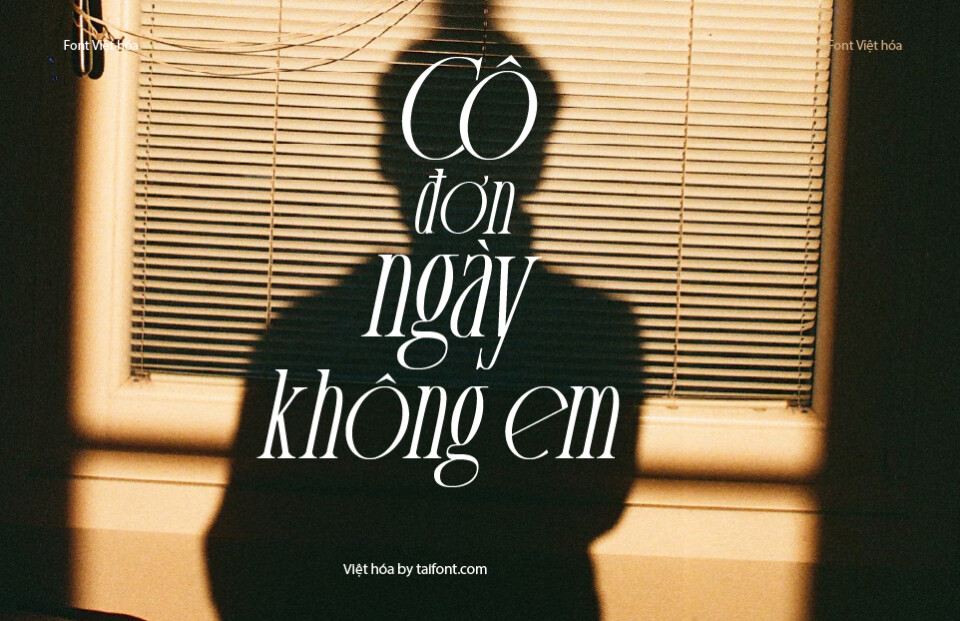
Font Việt hóa TF Sorena Italic
Font Việt hóa TF Sorena Italic – Nét Chữ Nghiêng Thanh Lịch Cho Mọi Thiết Kế
Giới thiệu về Font Việt hóa TF Sorena Italic trong sáng tạo đồ họa
Trong thế giới thiết kế đồ họa hiện đại, việc tìm kiếm một bộ Font Việt hóa TF Sorena Italic chất lượng là điều vô cùng quan trọng đối với các nhà sáng tạo. Font Miễn Phí luôn là nguồn tài nguyên quý giá giúp chúng ta hiện thực hóa các ý tưởng một cách chuyên nghiệp mà không tốn kém chi phí. Bộ chữ TF Sorena Italic vốn nổi tiếng với phong cách Serif tân cổ điển, khi được chuyển sang dạng nghiêng (Italic), nó mang lại một cảm giác thanh thoát, uyển chuyển và vô cùng tinh tế. Phiên bản Việt hóa giúp người dùng tại Việt Nam gõ được đầy đủ các dấu tiếng Việt mà không lo lỗi font, đảm bảo tính thẩm mỹ đồng nhất cho toàn bộ văn bản. Đây là sự lựa chọn hoàn hảo cho những ai đang tìm kiếm sự khác biệt và đẳng cấp cho dự án của mình.
Những đặc điểm nổi bật của Font Việt hóa TF Sorena Italic
Thiết kế Serif hiện đại kết hợp đường nét nghiêng mềm mại
TF Sorena Italic sở hữu những đường nét thanh mảnh, chân chữ Serif sắc nét nhưng không quá cứng nhắc. Khi ở định dạng nghiêng, các ký tự dường như có sự kết nối chặt chẽ hơn, tạo nên một nhịp điệu thị giác mượt mà. Điều này giúp bộ chữ trở nên cực kỳ bắt mắt khi được sử dụng làm tiêu đề chính hoặc các đoạn trích dẫn quan trọng. Độ tương phản giữa các nét thanh và nét đậm được tinh chỉnh kỹ lưỡng, giúp chữ vẫn giữ được độ sắc nét ngay cả khi in ấn trên các bề mặt chất liệu khác nhau.
Khả năng hiển thị tiếng Việt hoàn hảo
Một trong những điểm mạnh nhất của bản Việt hóa này chính là sự tỉ mỉ trong việc thiết kế các dấu thanh. Các dấu như huyền, sắc, hỏi, ngã, nặng được đặt ở vị trí cân đối, không đè lên các ký tự chính và giữ đúng tinh thần thiết kế gốc của tác giả. Điều này giúp người thiết kế tiết kiệm thời gian chỉnh sửa thủ công và tập trung hoàn toàn vào việc sáng tạo bố cục. Font chữ này hỗ trợ tốt trên nhiều phần mềm thiết kế phổ biến hiện nay như Adobe Photoshop, Illustrator hay Canva, mang lại trải nghiệm làm việc mượt mà nhất.
Ứng dụng thực tế của bộ chữ trong đời sống và học tập
Thiết kế thiệp mời, bìa sách và tạp chí
Với vẻ ngoài sang trọng, Font Việt hóa TF Sorena Italic thường xuyên xuất hiện trên các mẫu thiệp cưới, thiệp mời sự kiện cao cấp hoặc trang bìa của các cuốn tạp chí thời trang. Sự nghiêng nhẹ của con chữ tạo nên một không gian lãng mạn và đầy tính nghệ thuật. Trong môi trường học đường, các bạn học sinh và giáo viên cũng có thể sử dụng font này để làm đẹp cho các bài thuyết trình PowerPoint, giúp nội dung trở nên sinh động và chuyên nghiệp hơn, thu hút sự chú ý của người xem một cách tự nhiên.
Xây dựng bộ nhận diện thương hiệu cá nhân
Nếu bạn đang xây dựng một thương hiệu cá nhân liên quan đến lĩnh vực làm đẹp, nghệ thuật hoặc giáo dục, đây chính là giải pháp tối ưu. Chữ viết không chỉ để đọc mà còn để cảm nhận. TF Sorena Italic truyền tải thông điệp về sự chỉn chu, am hiểu và tinh tế. Việc sử dụng đồng bộ font chữ này trên các nền tảng mạng xã hội hay danh thiếp sẽ giúp khách hàng ấn tượng sâu sắc hơn với phong cách riêng biệt của bạn.